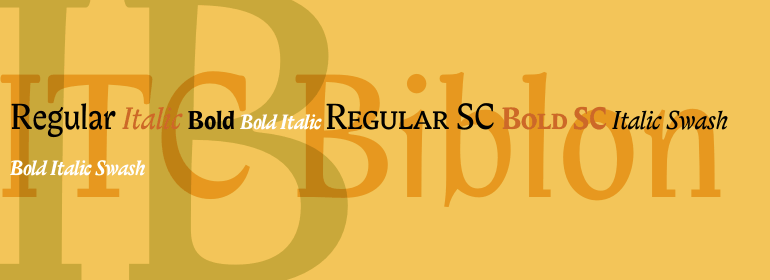
ITC Biblon®
ITC Biblon®,这款字体结构工整、笔画清晰,兼顾美观与易读性,适用于标题、正文、海报、包装、LOGO 等多种场景。字形优雅稳定,风格百搭耐看,适配日常排版与创意设计,让文字呈现更舒适、更具质感。ITC Biblon®一笔一画,皆是细节,以均衡的比例、流畅的线条打造舒适视觉体验,字形端正大气,风格简约现代。无论是商业设计、品牌宣传还是日常排版,都能轻松驾驭,让文字更有格调与力量。ITC Biblon®字体下载。